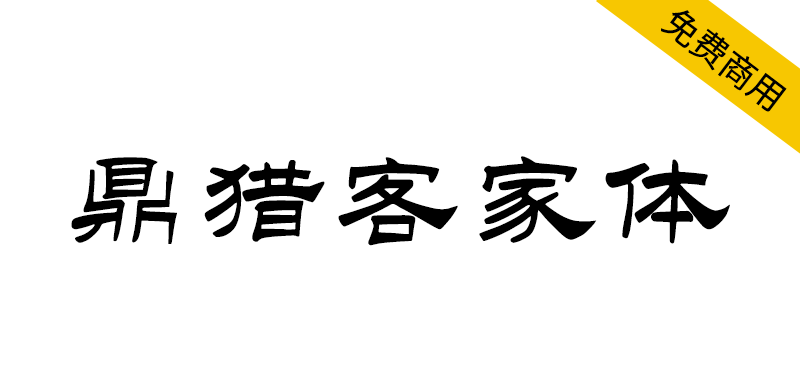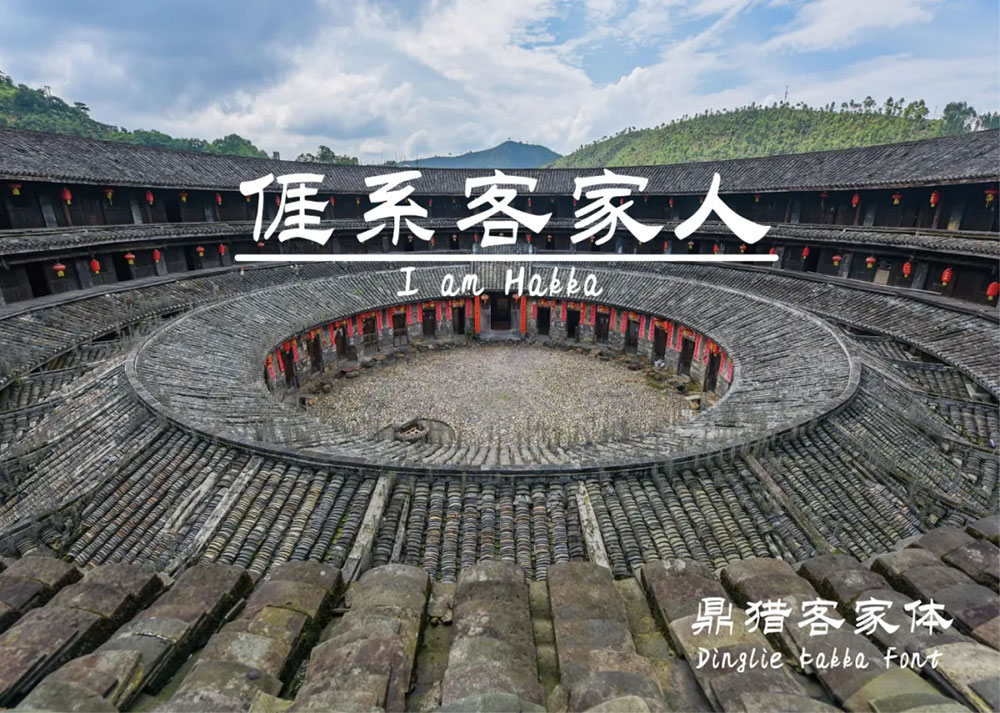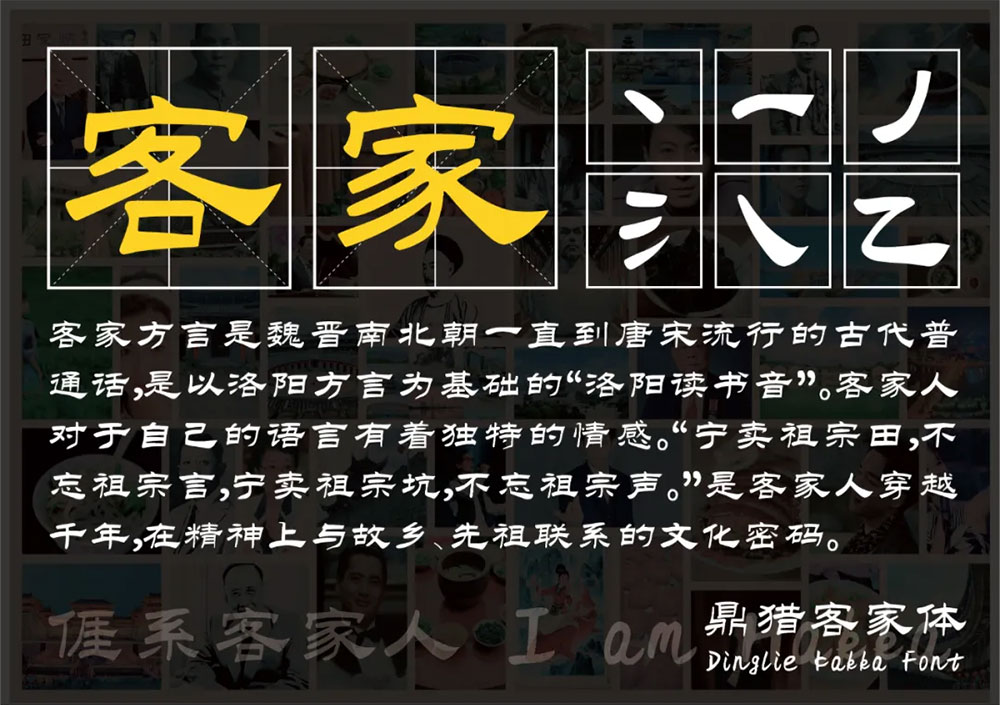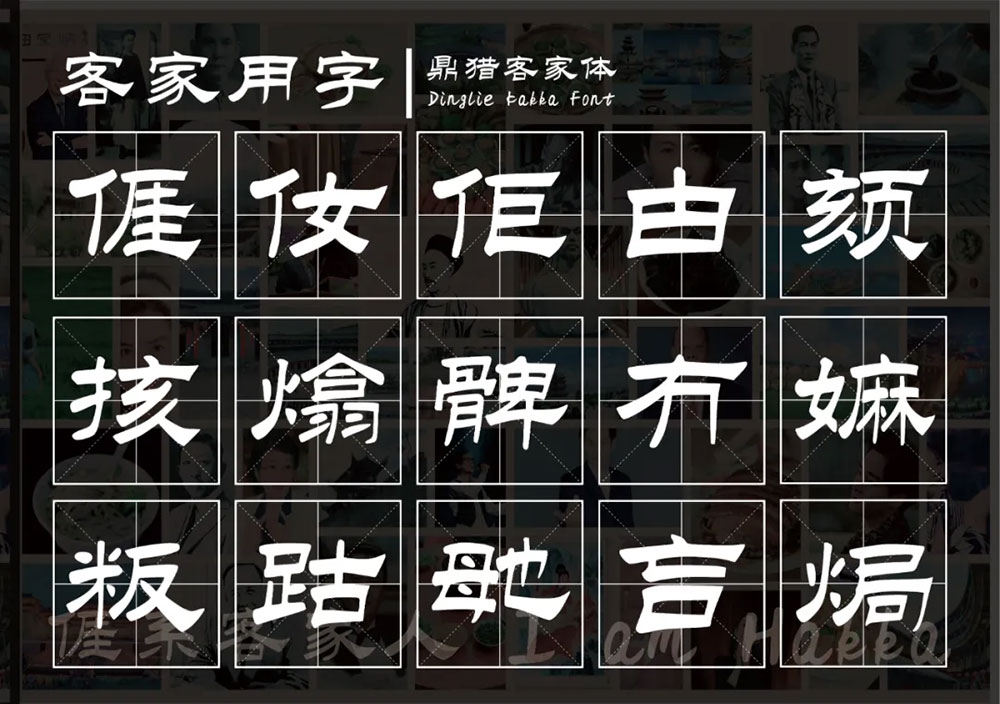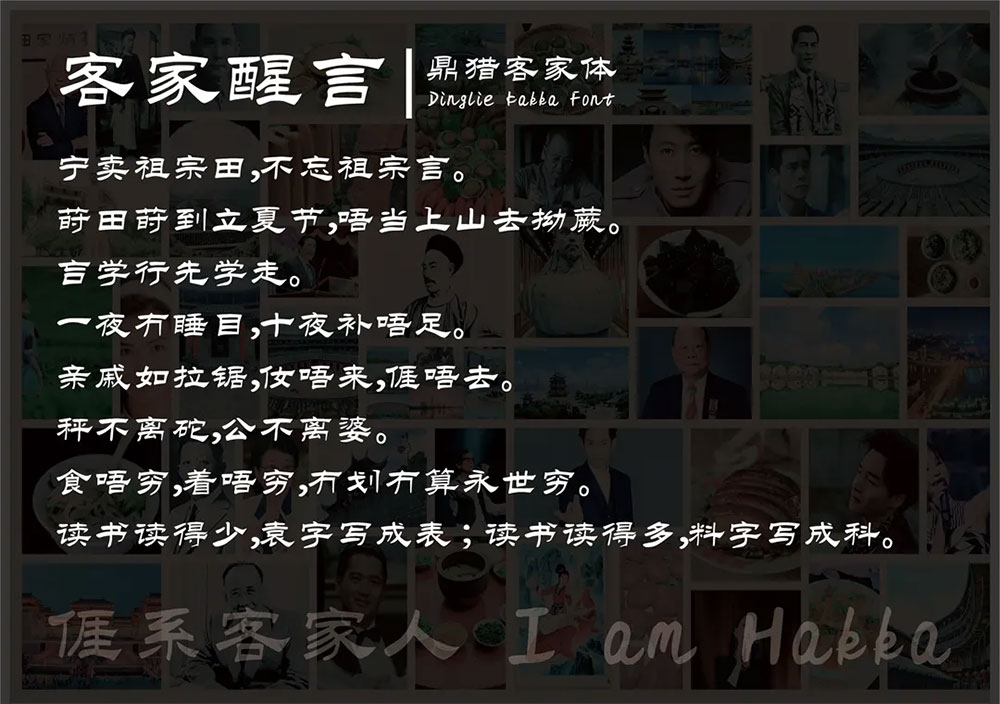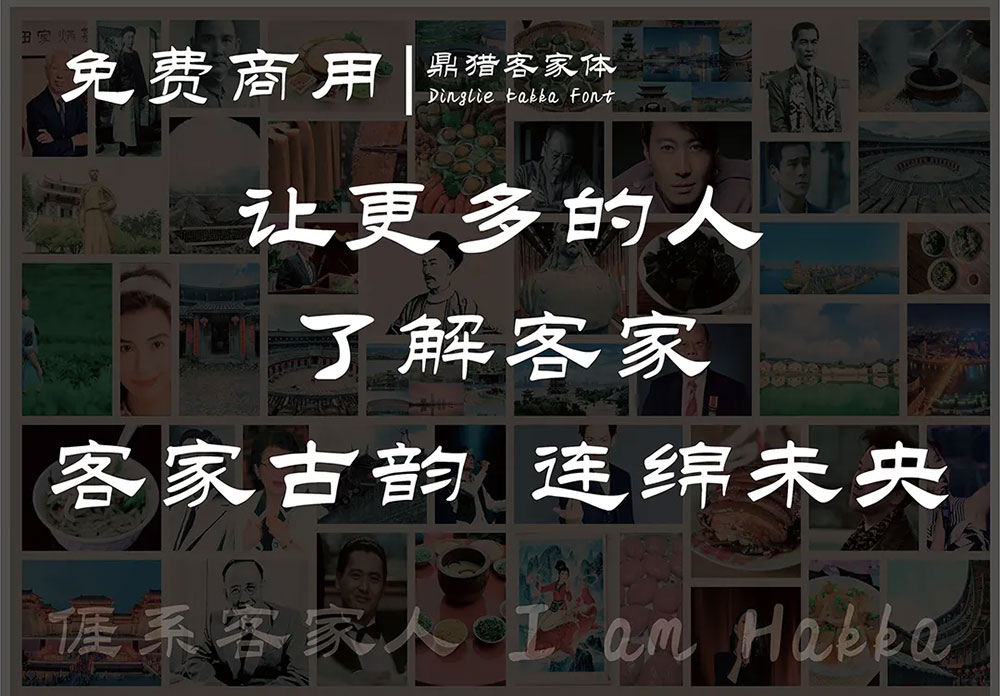
泱泱中华,屹立东方,客家民系,源远流长,祖传家训,字字华章,先贤教诲,子孙不忘。
抖落岁月尘封,回望魏晋风流。客家先民始于秦征岭南融百越时期,至宋朝逐渐南迁的汉人,在赣江、汀江、梅江冲击而成的三江平原上形成了客家民系。目前全球各处,全世界约有1亿客家人。五洲客家音,四海桑梓情。
鼎猎咨询作为客家民企,以富有中国文化底蕴距今1600年魏晋南北朝时期社会流行字体爨体字体为参照,设计出一套专属于客家人的字体——鼎猎客家体。
爨体字所具有的古韵、浑厚、拙朴特质,与客家文化相互交融。由此碰撞出专属于客家人的鼎猎客家体。鼎猎客家体(作品登记证书登记号:陕作登字-2024-F-00013784),是一套根据简体中文汉字编码国家标准(GB2312编码)设计的字体,并在此基础上一共设计了6789个简体汉字。
鼎猎客家体为一款原创字体,具有其独特的字形风格,适用于广告、书籍、海报等多个场合。其中,特别增加了客家话专属汉字数十个。
一声乡音,一盏乡肴,一生乡愁,化作一套鼎猎客家字体。嘱后裔继志述事,毋忘忠孝初心。